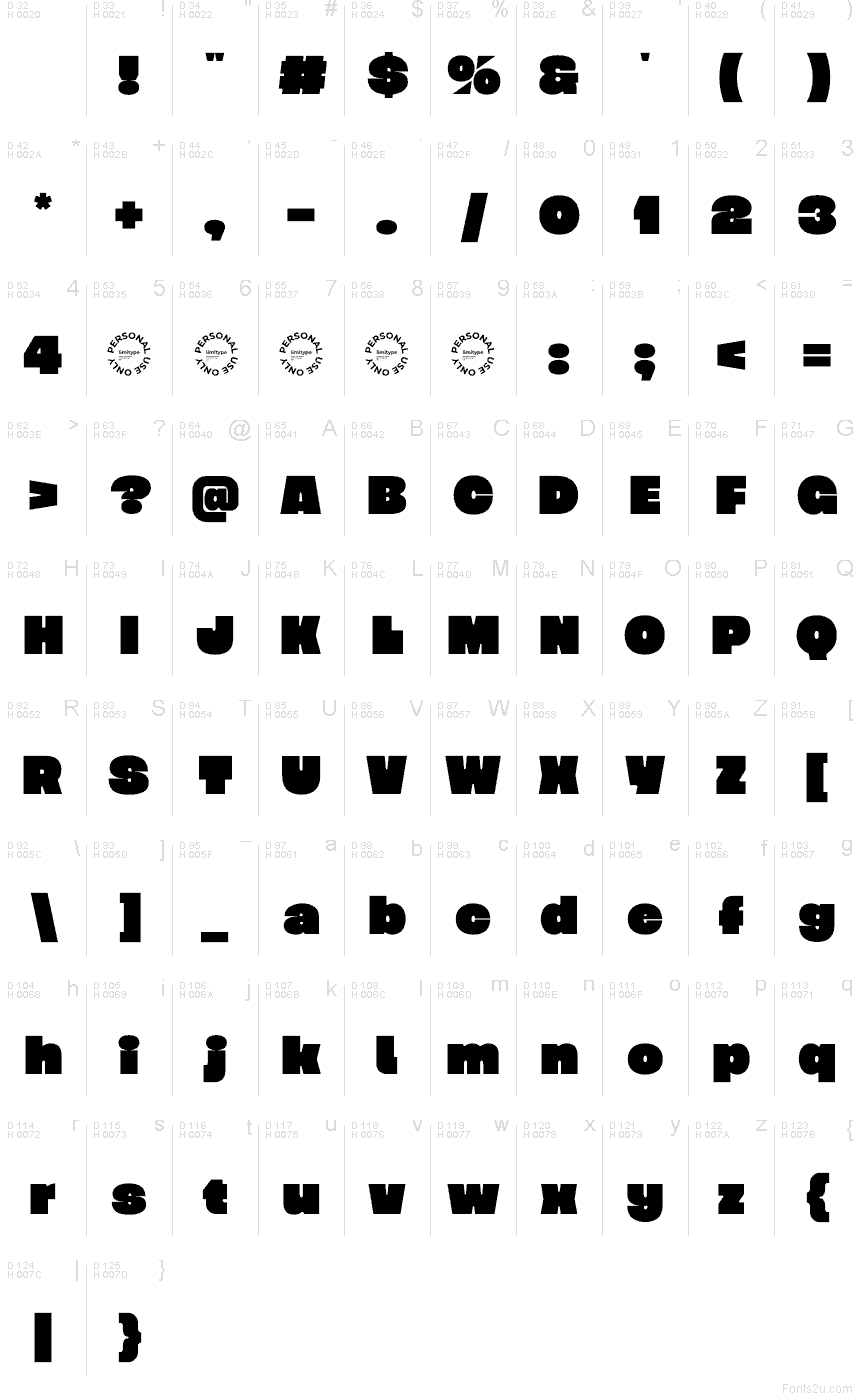
Aigon Bold de Limitype es una tipografía sans serif gratuita y ultra gruesa, con letras anchas, muy compactas y una contundente silueta display. Las formas suaves y redondeadas predominan en todo el diseño.
Las marcas de streetwear y de entretenimiento juvenil pueden aprovechar sus proporciones sobredimensionadas en logotipos, carteles y artículos de merchandising para conseguir un enérgico impacto de cómic. En el diseño para eventos, los espacios reducidos y las curvas exageradas logran que el título se integre como parte de la propia ilustración, semejante a una sólida figura recortada.